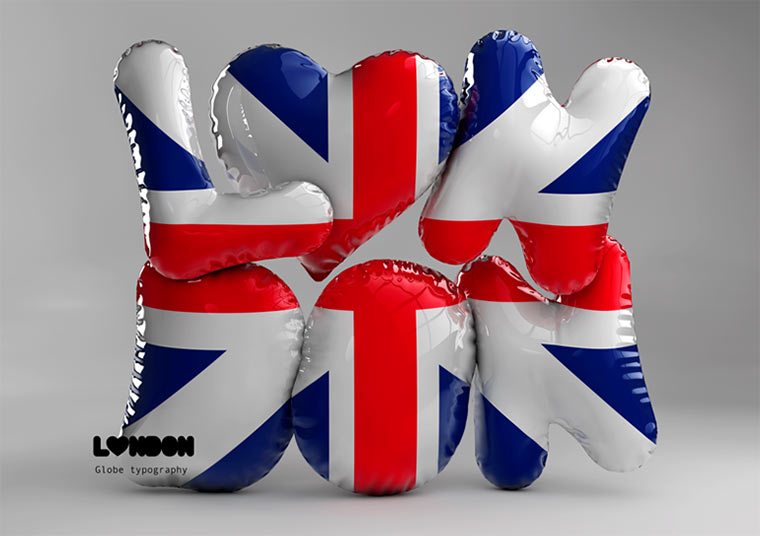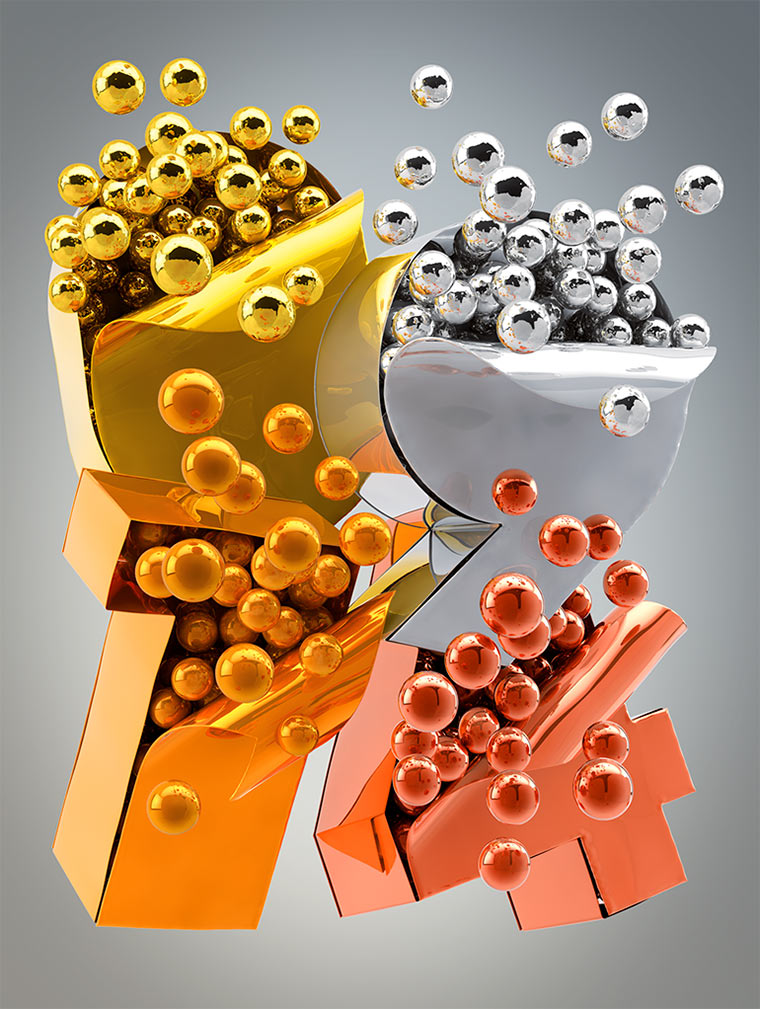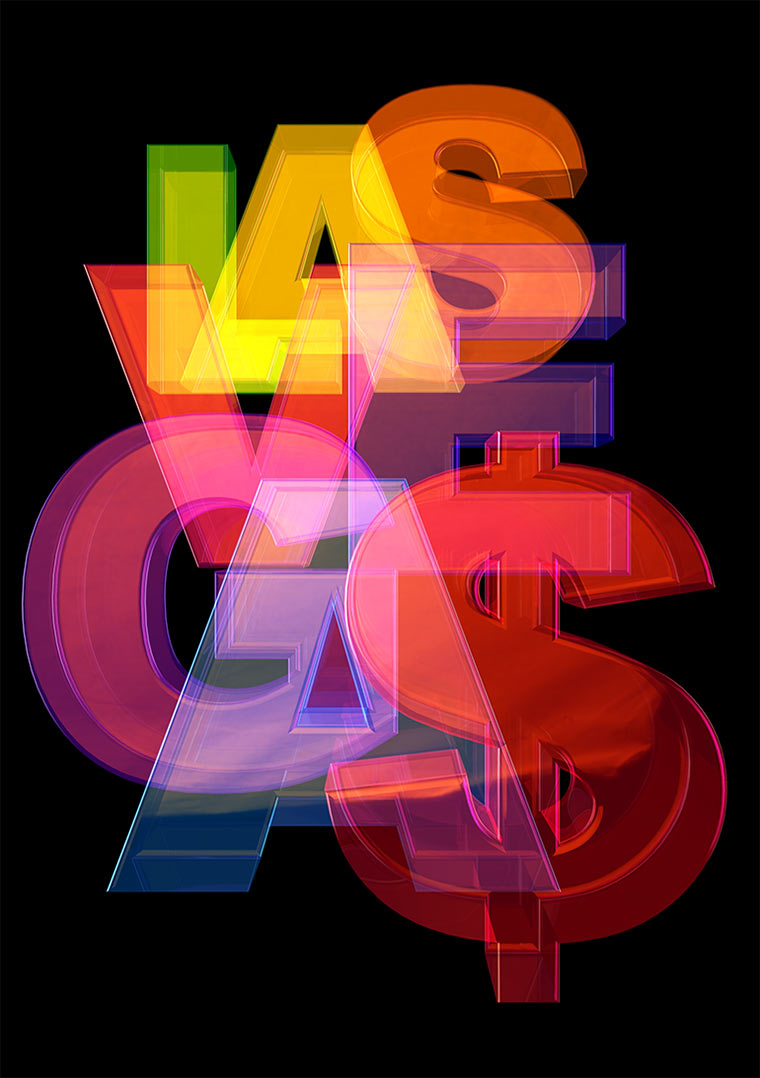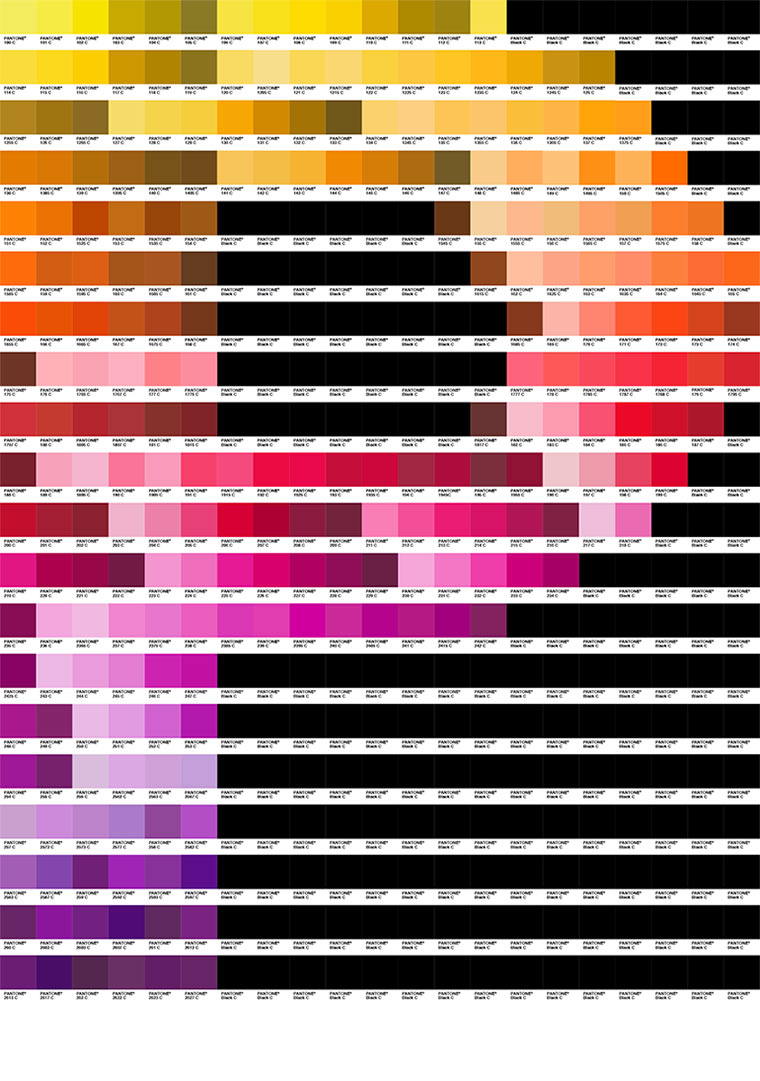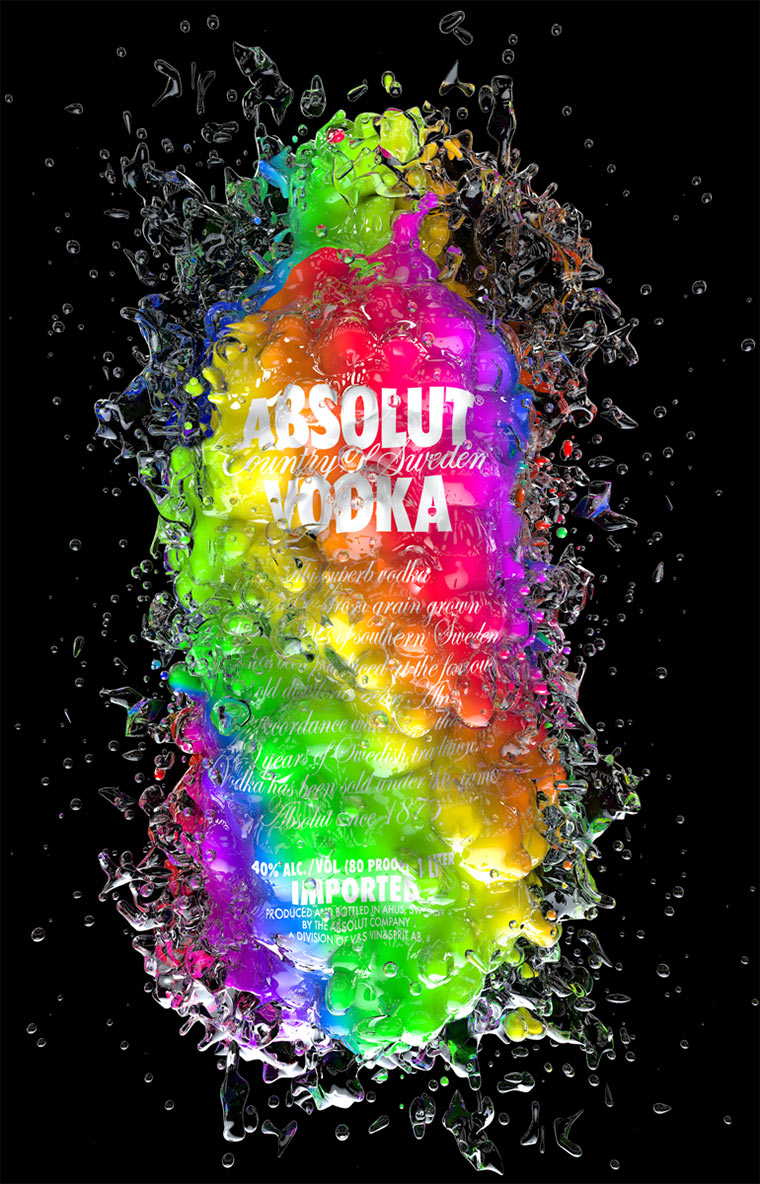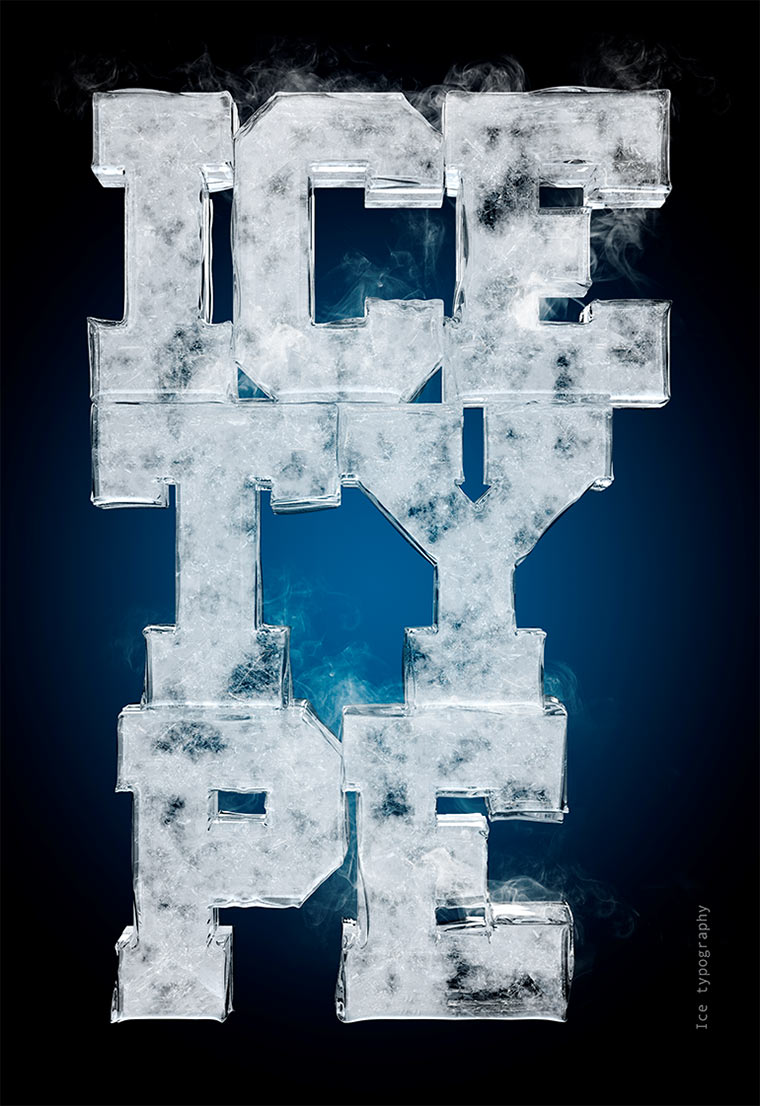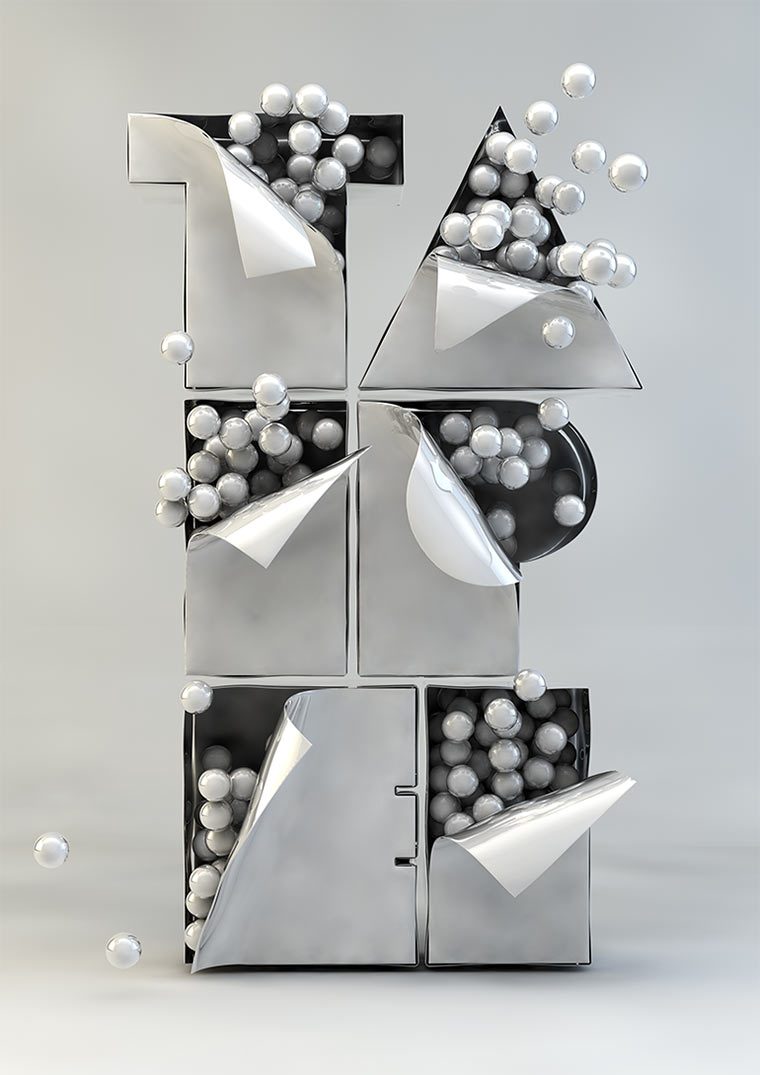
Kreative 3D-Arbeiten
Typographie: Txaber
Typographie: Txaber Txaber_01
Der Grafik-Designer und Illustrator Txaber aus Bilbao kann enorm spielerisch mit Buchstaben umgehen. Heraus kommen kreative Typografie-Arbeiten, die analog oder am Rechner in 3D entstehen.
„Experimentation is a constant in my work. They say everything is invented and I struggle every day to go against.“
Typographie: Txaber Txaber_02
Typographie: Txaber Txaber_03
Typographie: Txaber Txaber_04
Typographie: Txaber Txaber_05
Typographie: Txaber Txaber_06
Typographie: Txaber Txaber_07